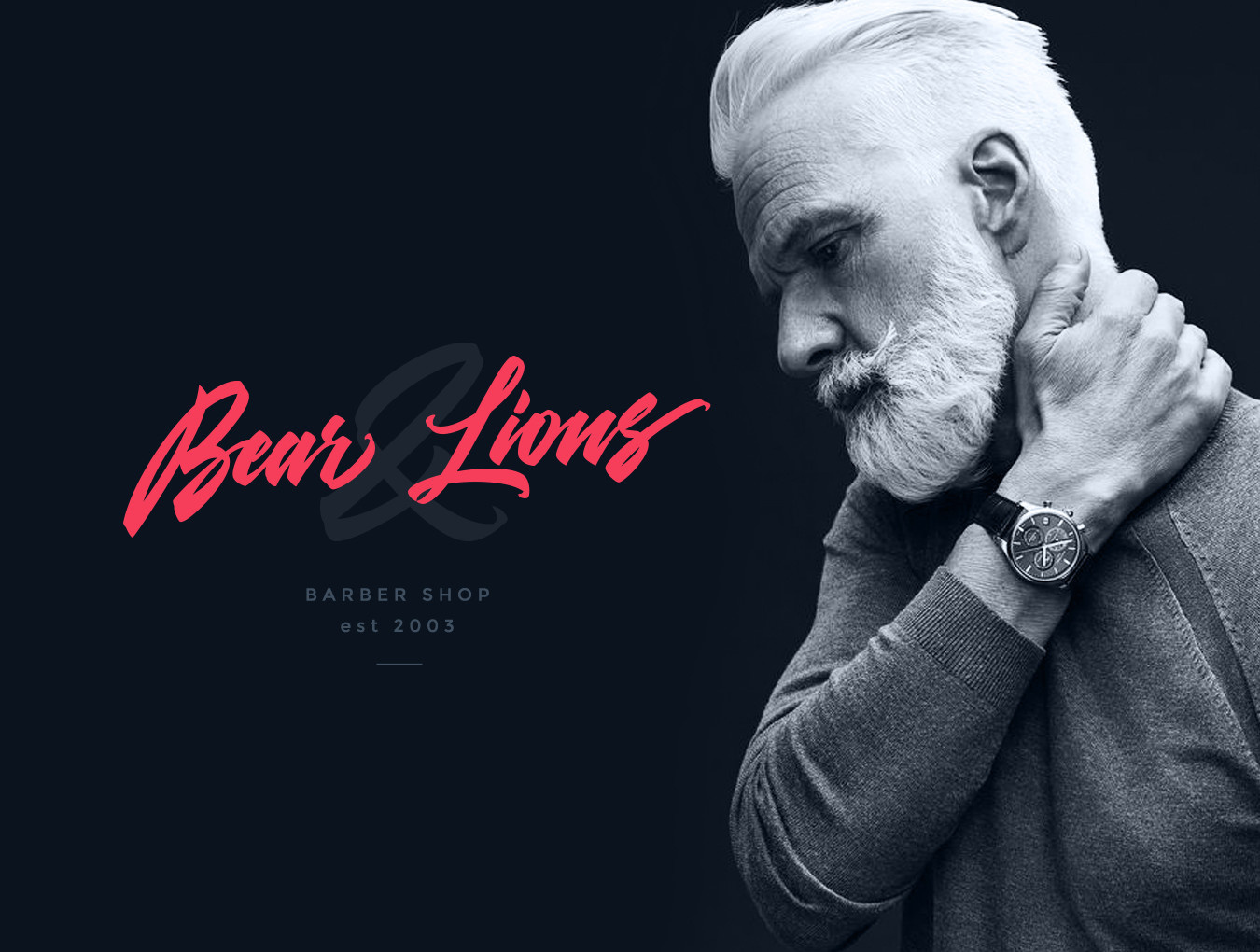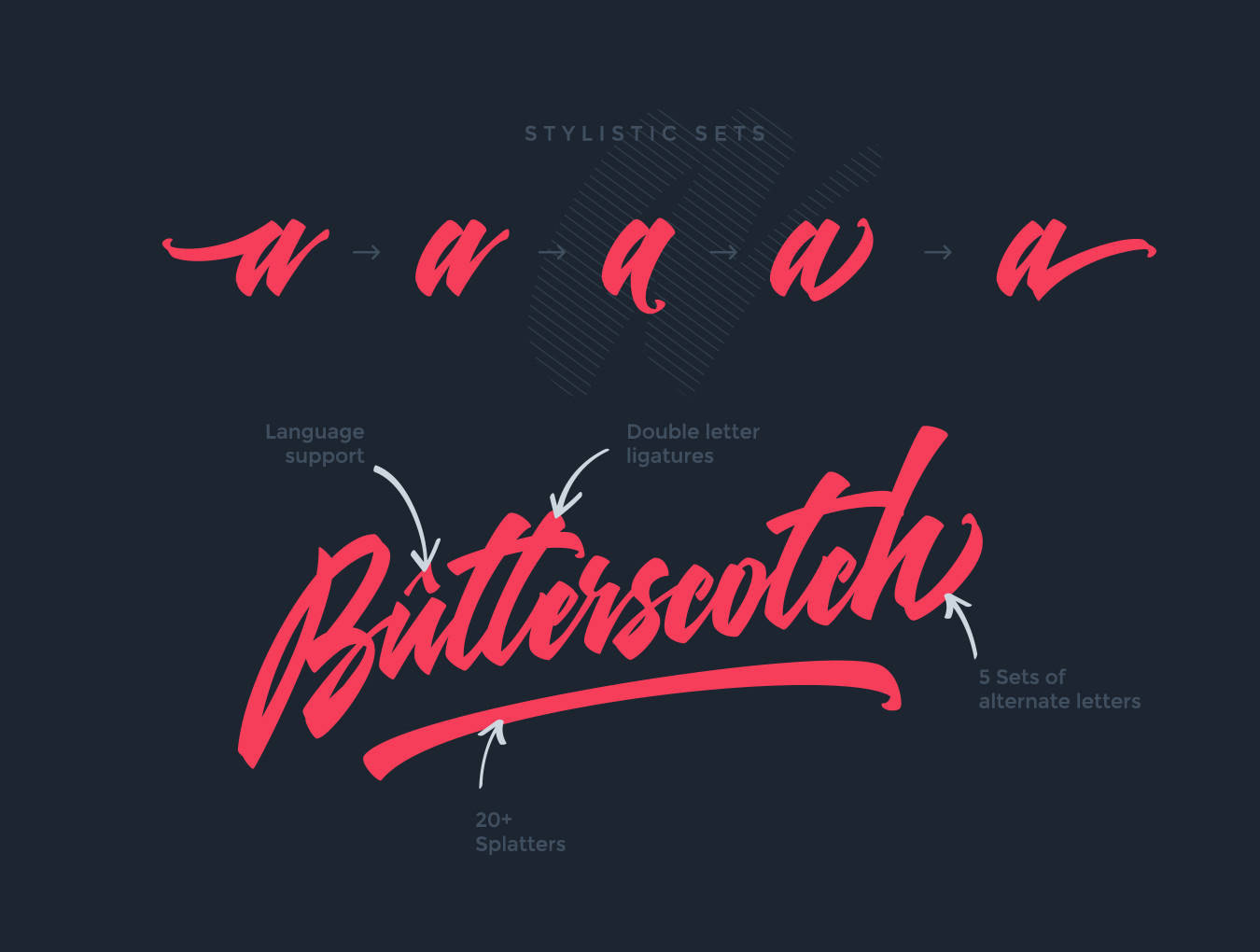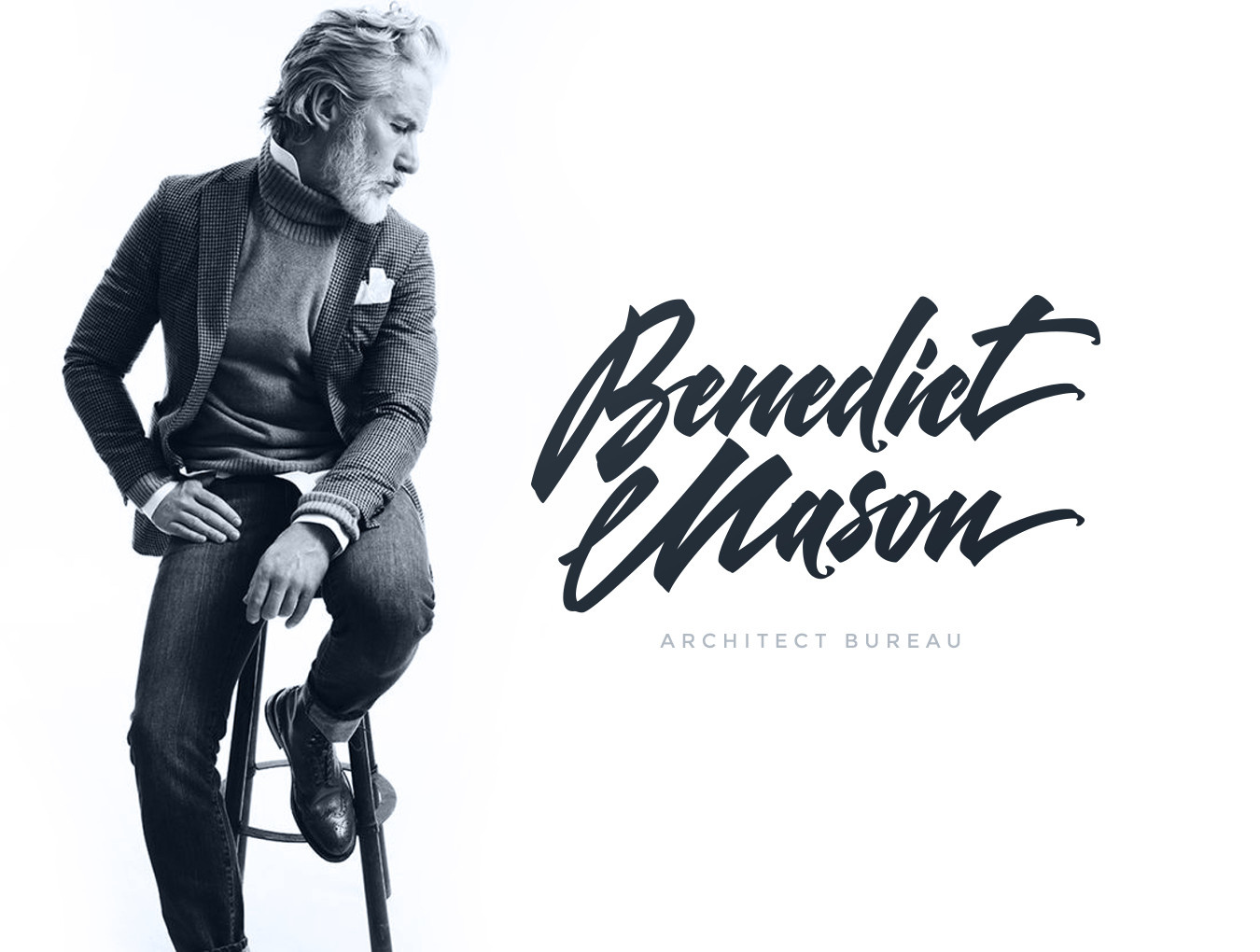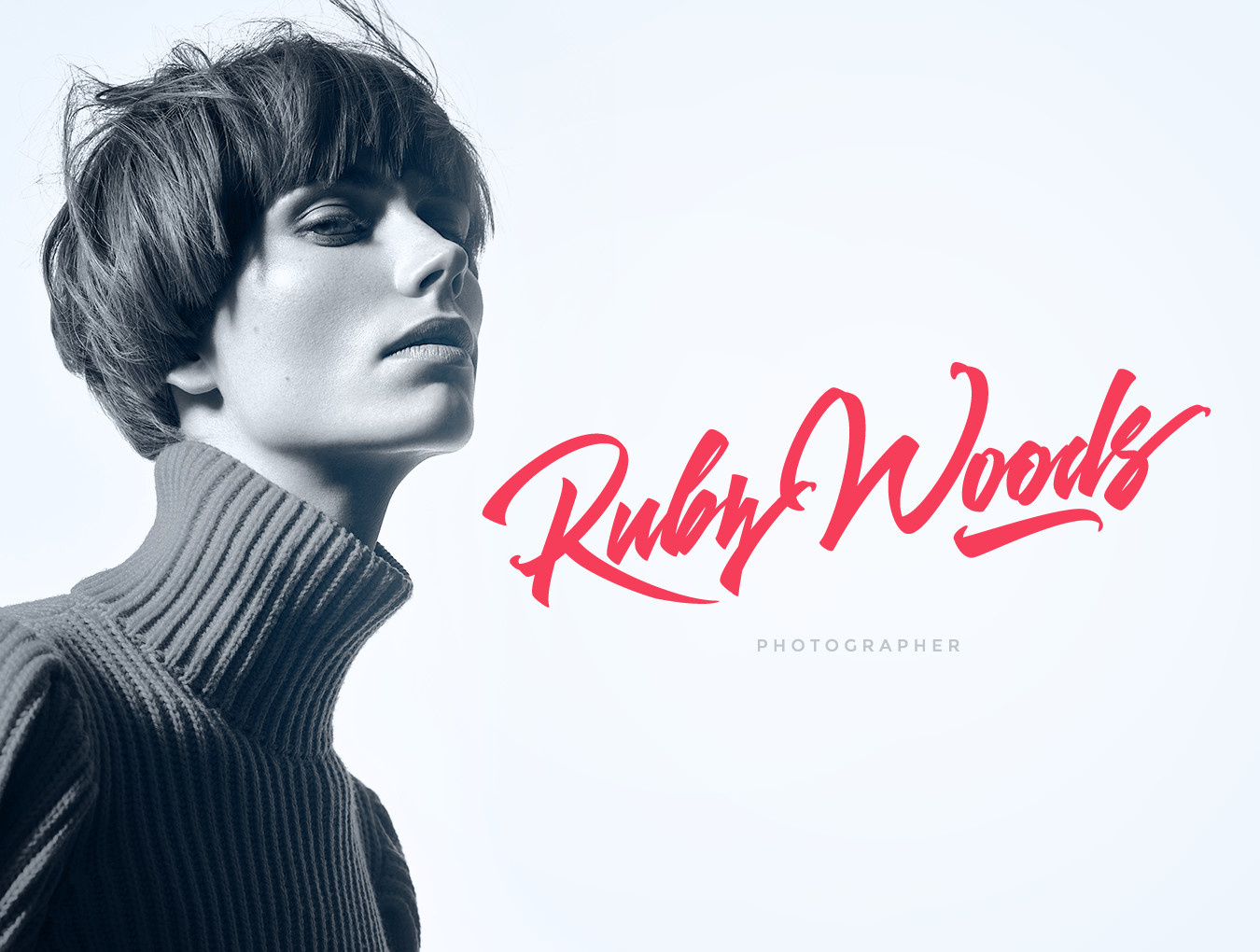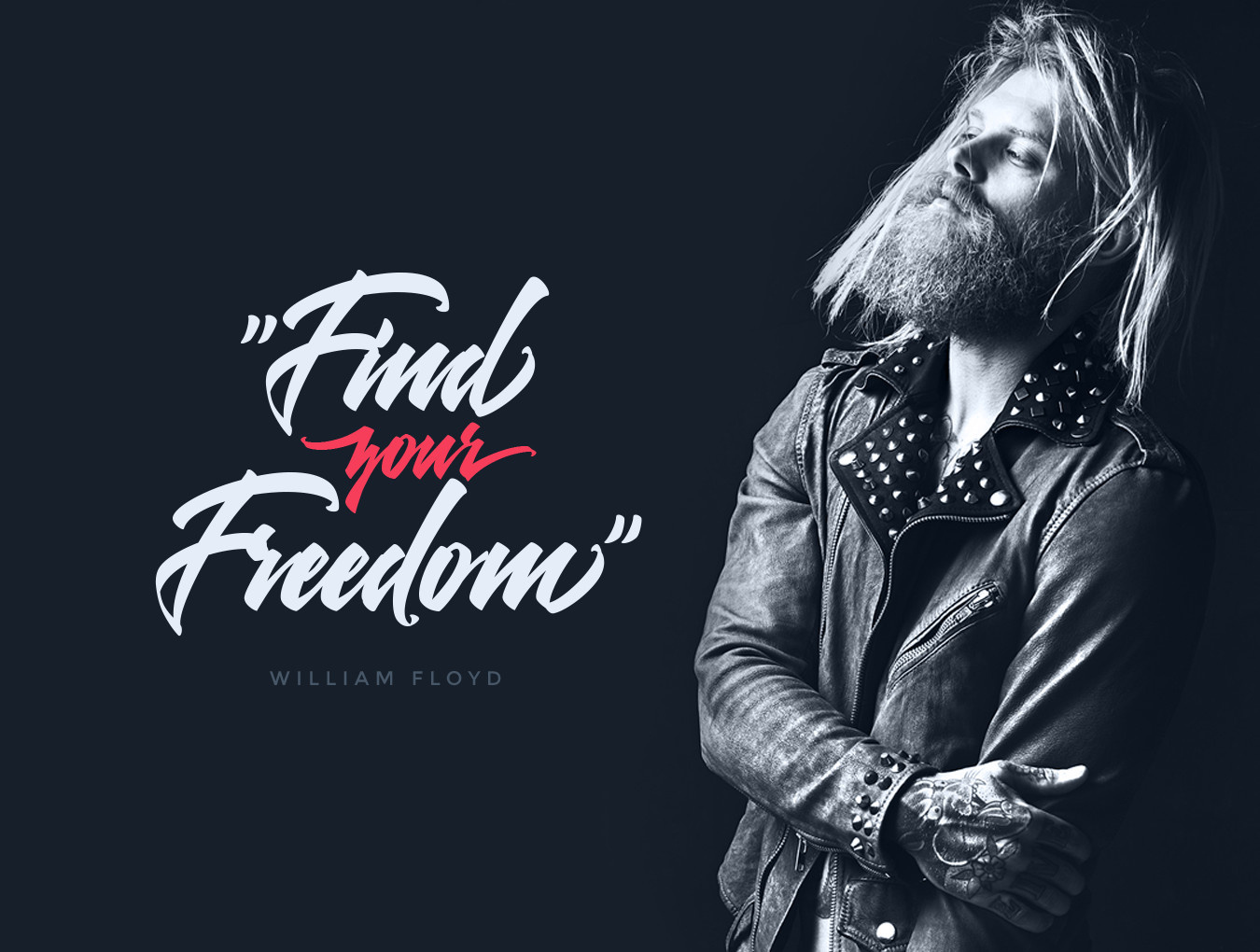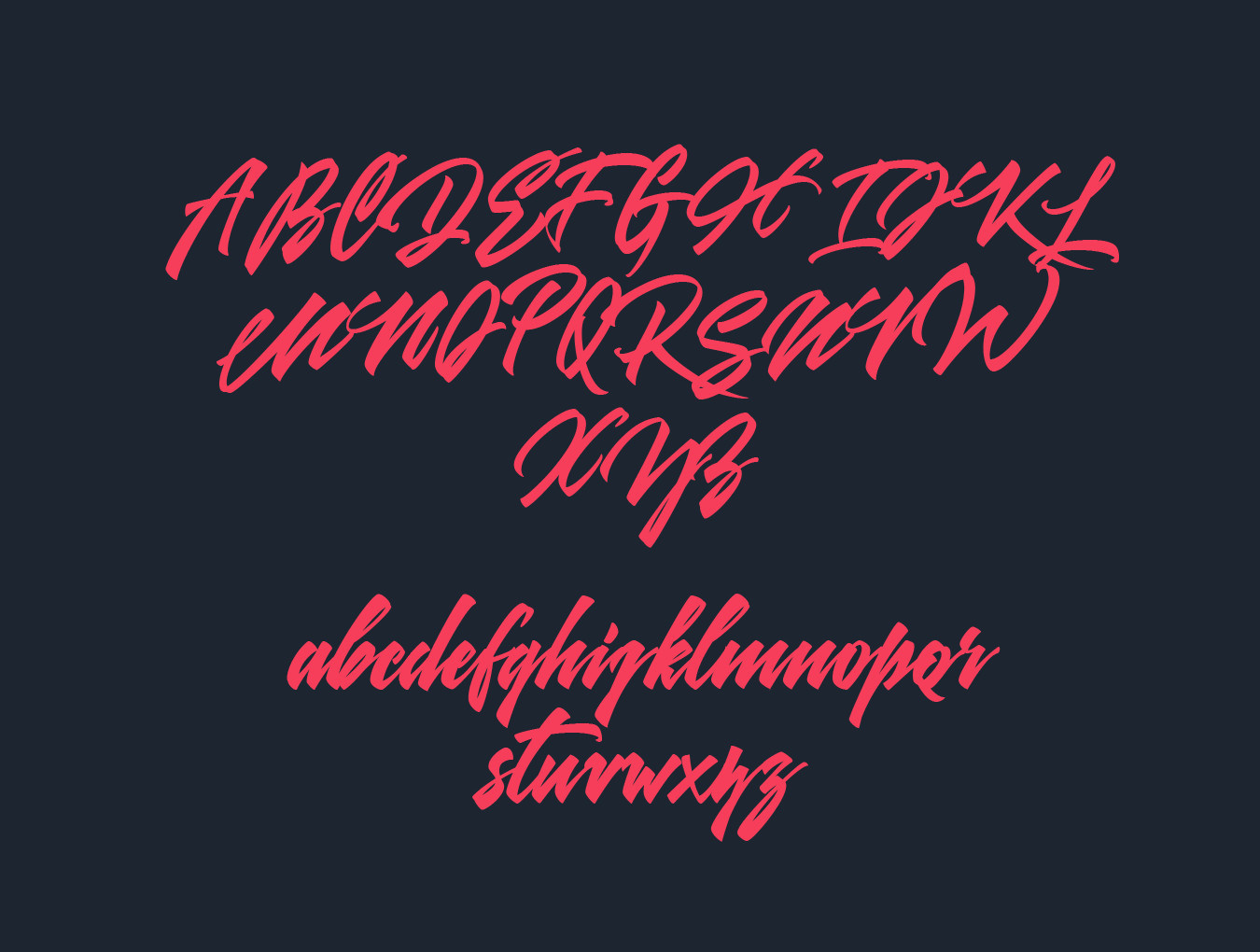
标志设计的优秀脚本字体,Emerald Script字体
Excellent Script based font for Logo design, Emerald Script Font
Emerald是徽标设计的字体包!此常规字体与备用字符组合使每个单词都是唯一的。然后添加Splatters字体作为标语和中提琴,这是理想的标志! Emerald Script Font有Emerald Normal OTF&TTF,Emerald Splatters OTF&TTF,Emerald Normal Webfont WOFF&WOFF2。